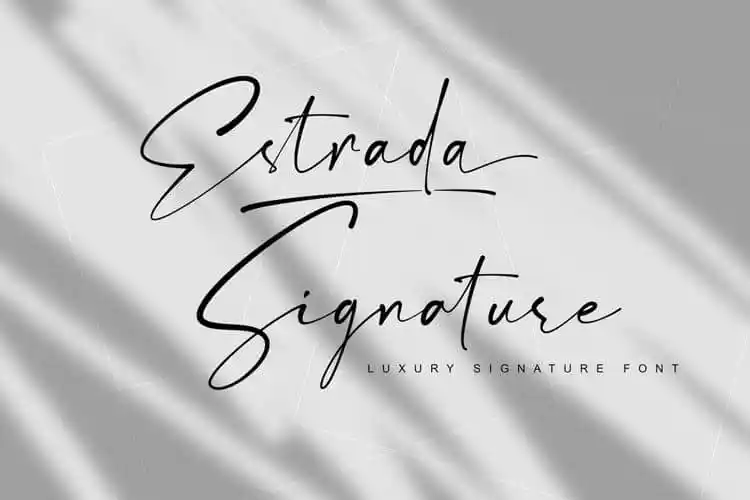
Estrada Signature Font
Introduzimos Estrada Signature Font, uma elegante tipografia feita à mão por drizy! O designer Lemonthe trouxe alternativas, estilos e ligaturas para essa beleza única. Esta é uma tipo de letra de luxo perfeita para todas as aplicações de branding, convites de casamento, embalagens de produtos, cartões de boas-vindas, posts no Instagram e muito mais. É a fonte certa para criar um estilo único em qualquer projeto visual, seja ele uma etiqueta criativa ou uma carta elegante. Obrigado à drizy! por compartilhar essa arte com o mundo da design.